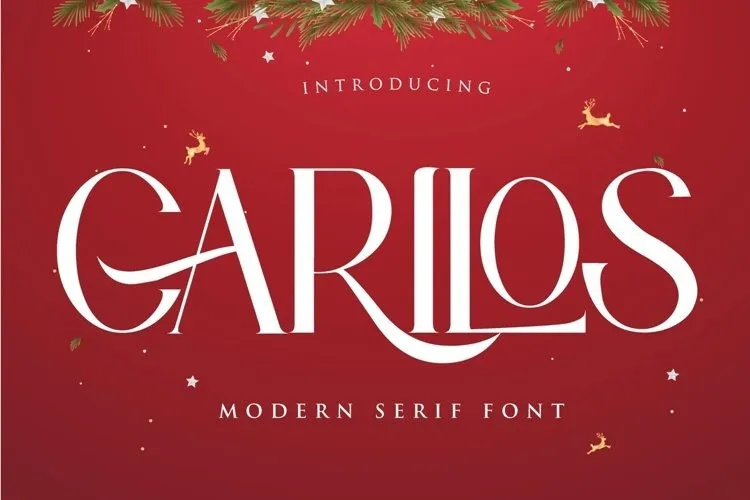
Carilos Serif Font – Download Grátis
A “Carilos Serif Font” é uma elegante escolha para quem busca um tom moderno mas sofisticado para seus projetos gráficos. Desenvolvida pela Gilar Studio, esta fonte serif incorpora elementos modernos e vintage na sua composição, resultando em um design que transmite elegância e classe. Indicada para uma vasta gama de aplicativos, como logotipos, cartas de cumprimento, citações, cartazes, marcação, cartões de visitas, assentamentos, títulos de design, cabeçalhos de blog, frases artísticas e tipografia, a “Carilos Serif Font” é uma ótima opção para quem deseja dar um toque único a projetos DIY ou de livros. Seu estilo convida à criatividade, permitindo que você realize qualquer tipo de projeto, desde designs inspirados em arte manual até trabalhos com efeitos de águacolor, tudo para tornar seus artigos gráficos ainda mais charmosos e atualizados.